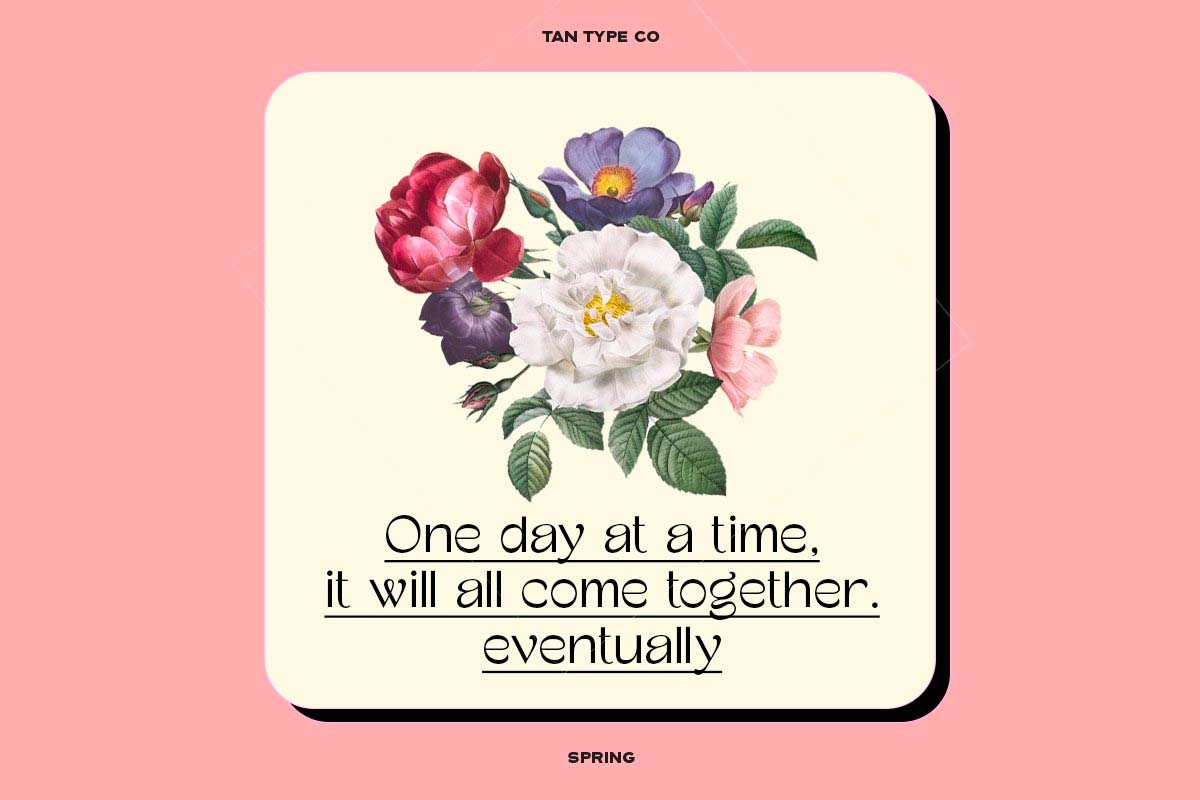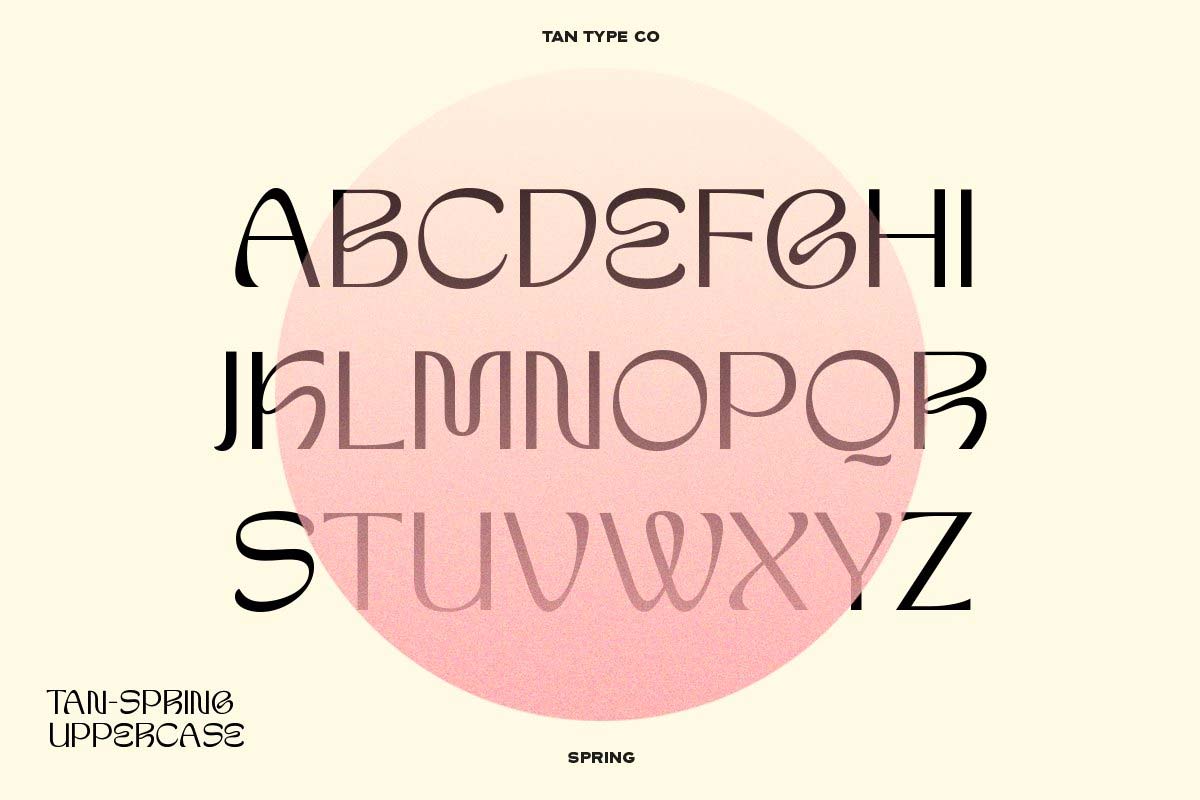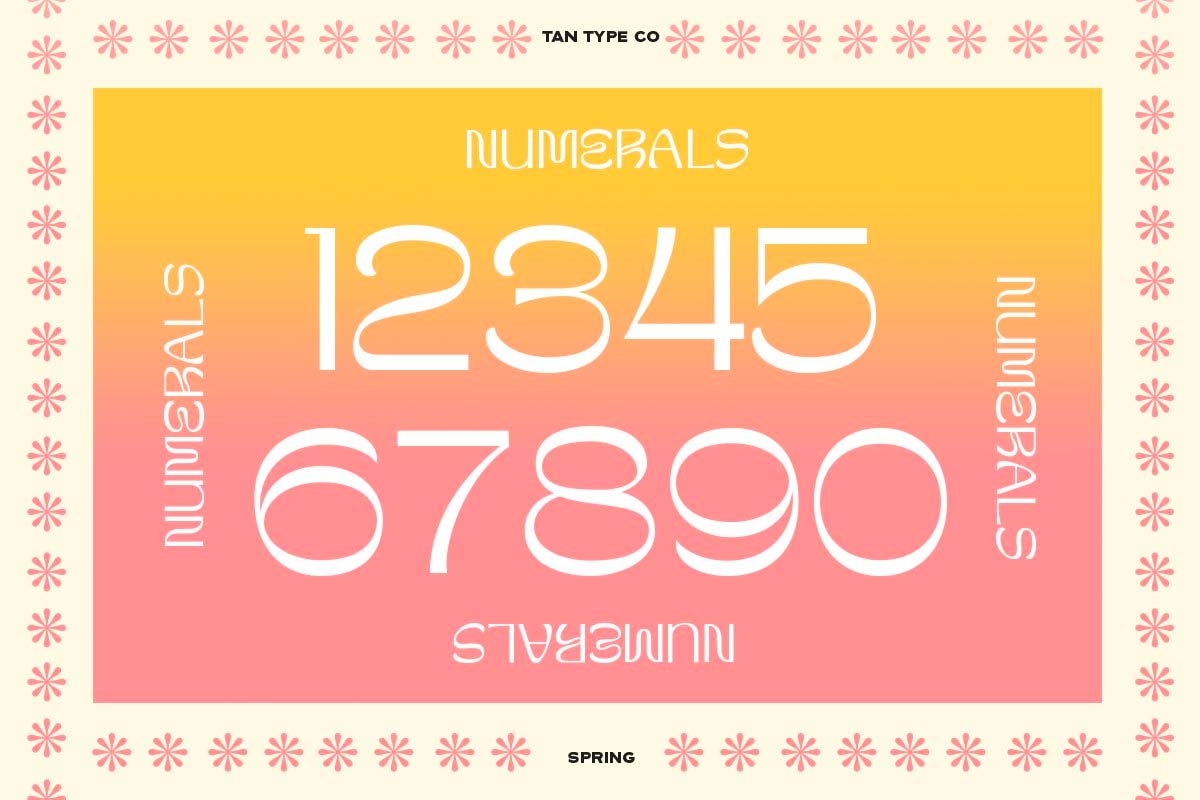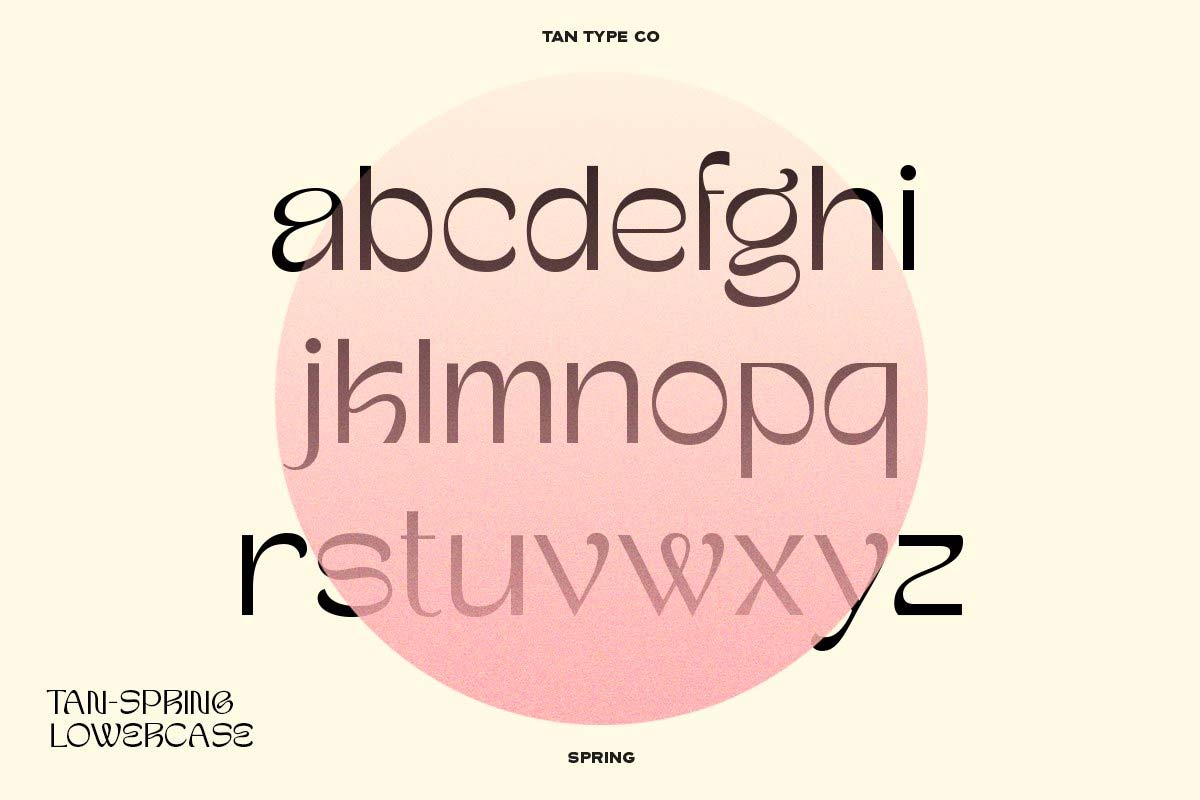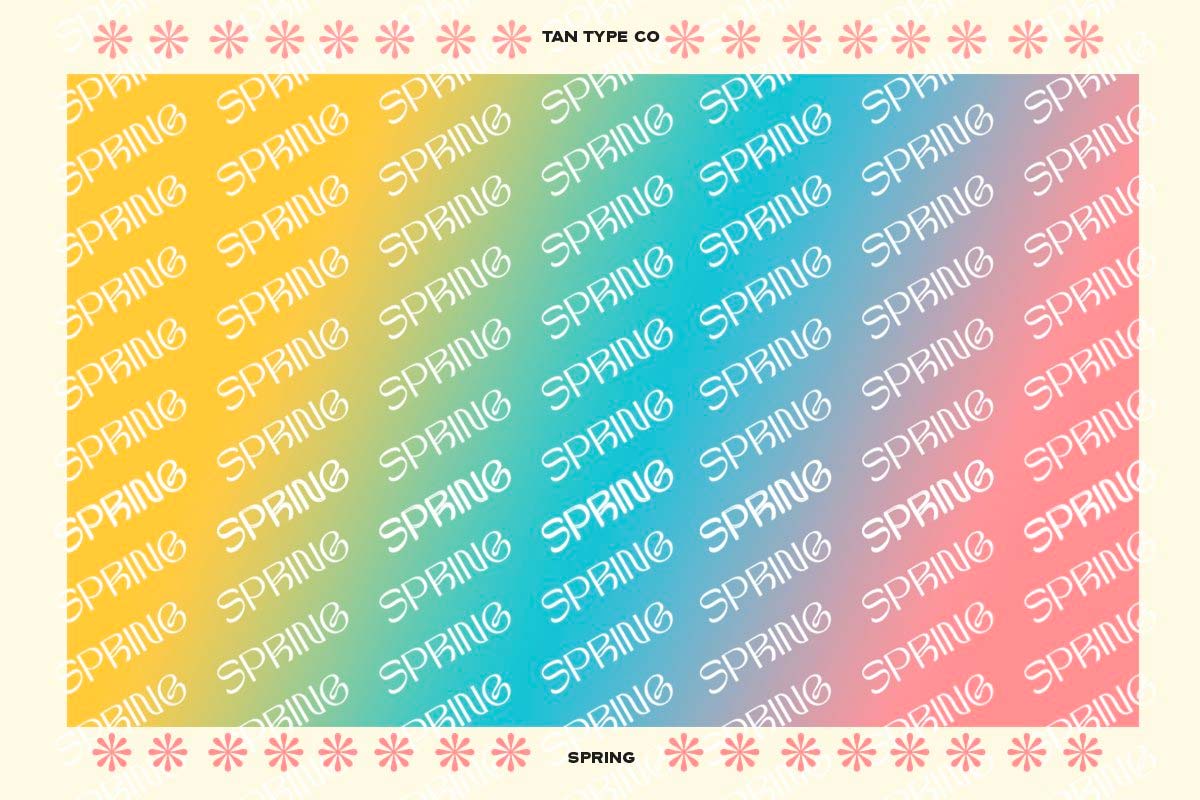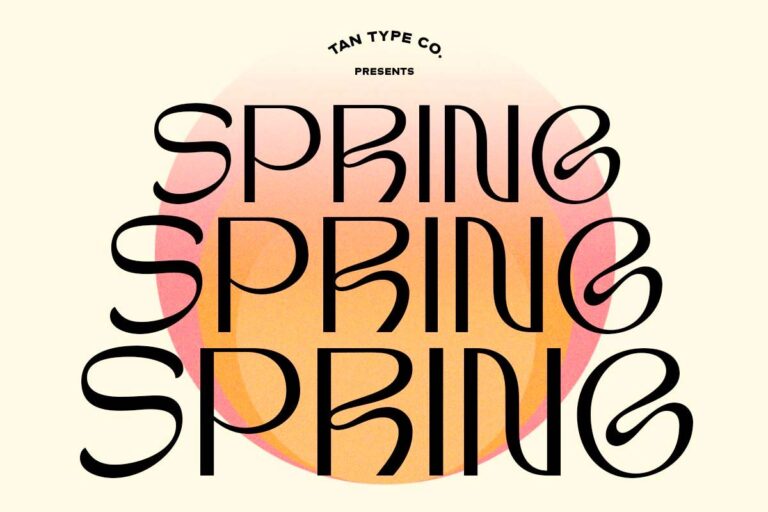
TAN – SPRING là một font chữ hiển thị được lấy cảm hứng từ phong cách retro. Nó có vẻ ngoài cổ điển nhưng vẫn có gì đó hiện đại với các nét chữ được thiết kế hình dạng gọn gàng với một chút đường rãnh ở các nét mang lại cảm giác hài hòa và đẹp mắt.
Tan Spring Font phù hợp cho rất nhiều các thiết kế khác nhau nó phù hợp cho cả những thiết kế hiện đại và cổ điển, có thể sử dụng làm tiêu đề, sản phẩm, tạp chí, quảng cáo, bìa sách, thư mời và nhiều hơn thế nữa.